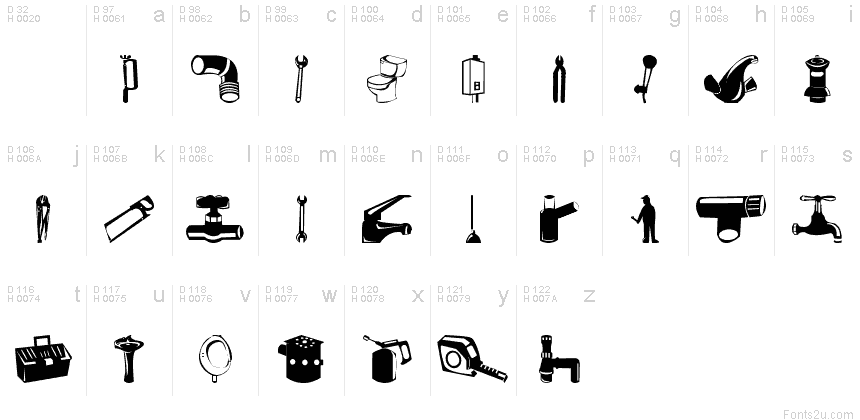
gasfiterbarrera Normal
david barrera agradece usar esta tipografia , ya que reune las variadas herramientas de un gasfiter y los elementos que repara a su vez.